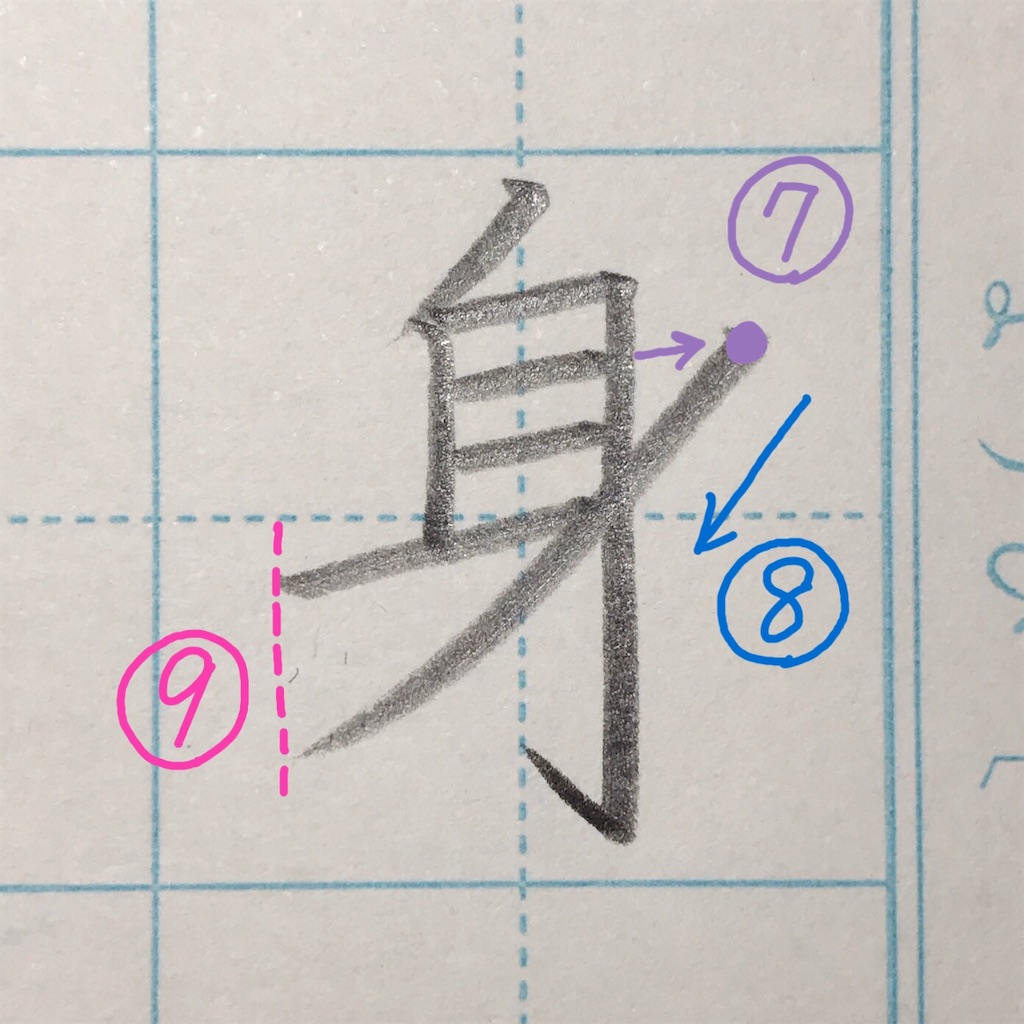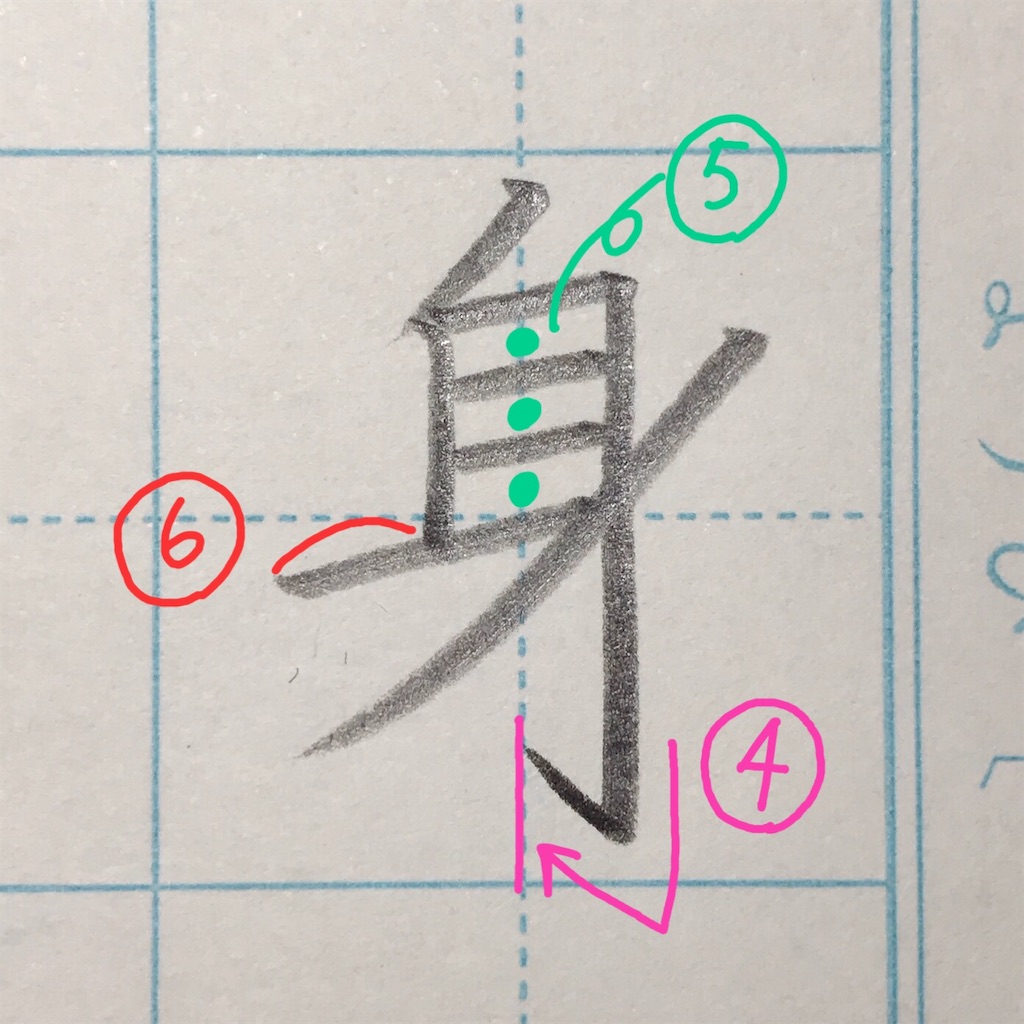
2020-02-04 「身」のきれいな書き方。 漢字 小3 →オンラインショップBASE 今回は「身」のきれいな書き方を解説します。 「身」の見本 「身」のポイント ①中心からスタート。45°の方向にシュっ。②縦画はまっすぐ、曲がらない。③横画は右上がりに揃える。 ④45°くらいでハネる。中心を越えないように。⑤間隔を揃える。⑥左を長く出す。 ⑦最終画は、4画目高さを揃える気持ちで。⑧45°の方向にまっすぐ、最後は気持ち良く払う。⑨大体揃える。 完成! お友達追加で、ひらがなのお手本プレゼント⭐︎